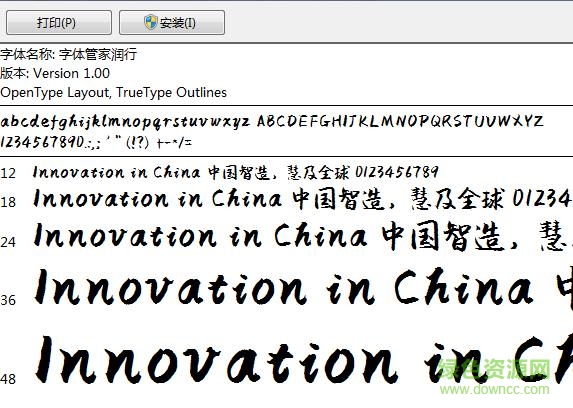
字體管家潤(rùn)行體是一款專為喜歡行書的朋友準(zhǔn)備的中文字體,該字體十分飄逸,彰顯了自己的個(gè)性,整體看上去非常的舒心,有需要的朋友歡迎下載使用!
字體管家潤(rùn)行體是字體管家打造的一款非常好看的行書書法字體,有著古風(fēng)飄逸和清爽灑脫感,讓字跡顯得干凈流暢不拖泥帶水,無論是書畫臨摹、海報(bào)設(shè)計(jì),還是廣告創(chuàng)意,都讓人有著極佳的視覺體驗(yàn),適用于很多領(lǐng)域!